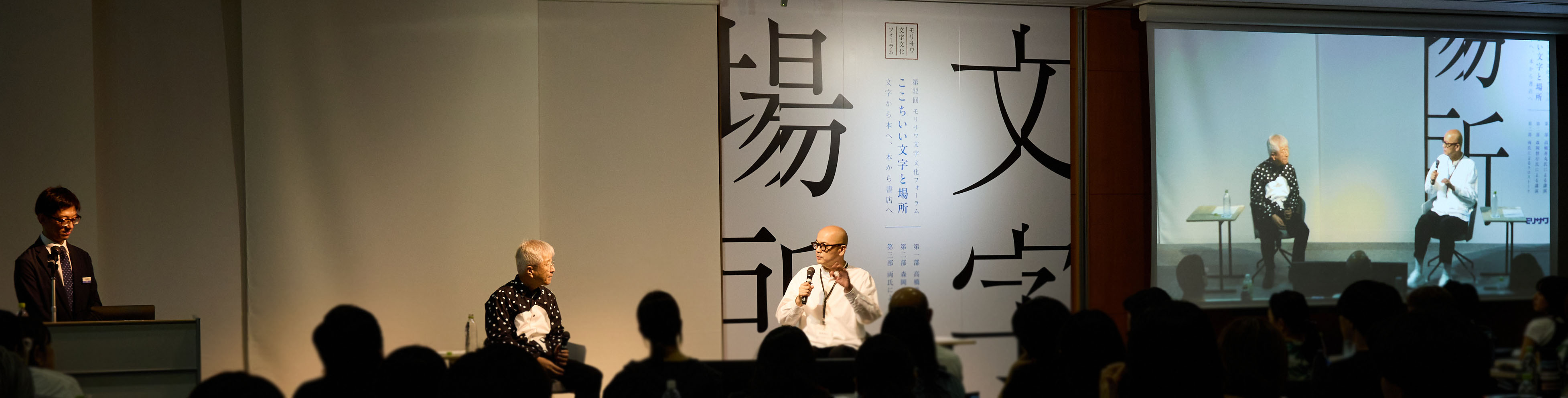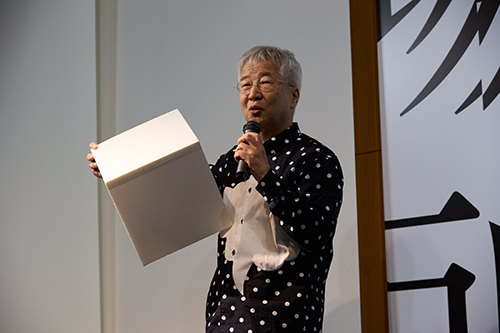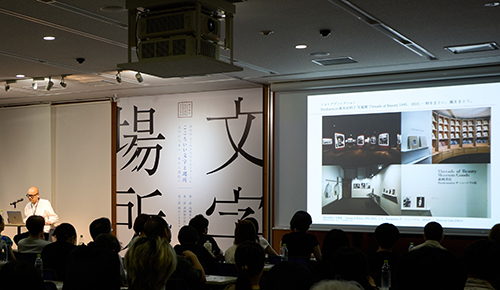
第32回モリサワ文字文化フォーラム 「ここちいい文字と場所 ―文字から本へ、本から書店へ」
2026年7月31日(金)、株式会社モリサワは第32回モリサワ文字文化フォーラム「ここちいい文字と場所 ―文字から本へ、本から書店へ」を開催。
エモーショナルなタイポグラフィを手がけるグラフィックデザイナー高橋善丸氏と「1冊の本を売る書店」をコンセプトとした森岡書店代表 森岡督行氏が登壇。
時を超え、空間を立ち上げ、人の心に鮮やかな情景を描き出す。そのリアリティはいったいどこに宿るのか。「文字デザイン」と「本」を起点に、人の思考や感覚を通して生まれる「ここちよさ」の本質を、独創的な視点から探る。新たな発見に満ちた密度の高いフォーラムとなった。
講演者
高橋 善丸(グラフィックデザイナー)
森岡 督行(森岡書店 代表)
第1部 高橋 善丸氏 「文字から、想像を促すデザインへ」
高橋氏は「文字から、想像を促すデザインへ」をテーマに据え、文字とビジュアルデザイン、2つの観点から話を進めた。
機能性・先進性・情感が生み出す文字表現
文字デザインの基本要素は読めること(可読性)をベースとし、そこに読みやすい形や安定した美しい形、長く読んでも疲れないといった「機能性」、新しさや独創性といった「先進性」、楽しさや表情などの「情感」の3つがバランスよく成立したところに「見て読んでここちいい文字」ができるという。
文字は情報を超えて情景を伝える
文字造形において、グリッドを基本としながら、線や交点の強調、有機的な曲線、文字の本質だけを残す簡略化などを取り入れることで、文字に意味や情景を与える表現を紹介。文字に感覚情報を加えることで、記号を超えた豊かな視覚表現が生まれる。「文字というのは理解のコミュニケーションツールだが、文字デザインというのは、感覚情報を盛り込むことで、記号性を遥かに超えた視覚情報が情景を伴って伝わる感覚のコミュニケーションである」と語った。
想像を促すデザイン
ここで本題に入っていく。
6面あるはずが実は3面しかない立方体や、白紙に雪を被った電柱を描くことで余白が雪原だと感じる作品を見せ、「情報をすべて与えなくても、想像のきっかけとなる要素があれば、見る側が頭の中で情景を補う」と語った。
「シンプルな表現でリアリティを出すとは、少ない表現要素で受け手の経験や既知の情報を引き出し、そこから多くのイメージを連想させることで、伝えたい内容をより豊かに広げる」。
さらに、一本の線やぼかした文字だけでも、人は地平線や奥行き、空間を感じ取ることができる。「リアリティというのは、写実的な映像を見せることではなく、どう相手の想像力を持ってリアリティを感じさせるか」と述べた。
想像を促すコミュニケーションデザイン
ここからは「想像を促すコミュニケーションデザイン」をテーマに、文字デザインによって見る人の想像力を引き出す手法や作品が紹介された。
二次元の文字から立体や空間を想像させた作品、影や水面の揺らぎによって時間や情景を連想させる表現、点や線、欠けた文字など、脳が最小限の情報を使って不足を補おうとする心理を利用した作品などが紹介された。さらに、「カニッツァの三角形」や「パレイドリア現象」などの視覚・心理効果を応用し、一つの作品に複数の意味を持たせる手法を解説。特定の視点からだけ文字が現れる「アナモルフォーシス」の技法を活用したインスタレーションでは、空間そのものをコミュニケーションの媒体にする可能性を示した。
高橋氏は、「相手の既知情報を利用し、イメージのきっかけを与えれば、脳に映像をつくりあげてくれる。はっきりと直接的な表現を避ける独特な日本的コミュニケーション方法を、私はグラフィックデザインで表現している」と語り、講演を締め括った。
第2部 森岡 督行氏 豊かさを伝えるための「1冊の本を売る書店」
森岡氏は「戦争や争いではなく、デザインや美しいものといった世界の豊かさに接続して生きたい」との思いから「1冊の本を売る書店」を始めた。毎週1冊の本を軸に展覧会を開き、著者や編集者、デザイナーと読者をつなぐ場をつくっている。
書店が入る東京・銀座の鈴木ビルは、かつて亀倉雄策らが活動した「日本工房」の拠点だった。その歴史に惹かれて入居し、ビルの住所を取り入れたロゴやオリジナル書体も制作した。
また、日本工房が句読点を省く誌面づくりを試みていたことを紹介し、文字デザインが試行錯誤された黎明期を振り返った。
人との出会いが未来をつくる
森岡氏は、展覧会の企画をきっかけに会いたい人へ自ら会いに行けることが仕事の醍醐味だという。著者や編集者、クリエイターとの出会いはすぐに成果につながらなくても、後に新たな仕事へ発展することがあり、その連続が「未来をつくる」と話す。
また、モリサワ創業者・森澤信夫が講演に感銘を受け、自ら星製薬の星一を訪ねた逸話を紹介し、自ら行動することの大切さを伝えた。
森岡書店では、1冊の本に合わせて店全体の空間をつくり変え、本の世界観を表現している。著者から人生や作品の背景を直接聞けることが、仕事を続ける原動力になっていると語った。
想像力が生み出す「ここちいい場所」
写真家ソール・ライターの蔵書を調査した際、本人が実際に訪れたことのない日本について、本の余白に「1972年に日本を訪れた」と書き込んでいたことを知る。
森岡氏は、その書き込みによって、頭の中で日本へ行ったかのような体験が作られたのではないかと推測し、胸を打たれた。
そして、高木由利子氏のモノクロ写真では、衣装や素材、色彩を鑑賞者自身が想像し、写真との対話が生まれるという。現実の場所でなく脳内で作られたものも、今回のテーマ「ここちいい文字と場所」と言えるのではないかと語った。
紙の文化の可能性
展覧会の世界観を丁寧に落とし込んだ12,000円の図録が約1,600冊売れたことを挙げ、紙の媒体には今なお大きな価値があると語った。デジタル化が進む一方で、日本には雑誌などの豊かな出版文化が根付いており、MoMAのキュレーターもその価値に注目しているという。紙媒体の衰退だけに目を向けるのではなく、その文化を大切に受け継いでいきたいと話した。
独自性が新しい価値を生む
「1冊の本を売る書店」は世界でも前例のない取り組みとして海外から注目を集めた。しかし、日本語の本を読めない来店客から「せっかく来たのに本を買えない」という声が寄せられた。そこで森岡氏は、本を購入した人に似顔絵を描くサービスを始めた。これがインフルエンサーの紹介をきっかけに話題となり、店の前に観光バスが横付けされるほどの人気を集め、中国での講演依頼にもつながった。
深圳での講演で「新しいアイデアはどのように生まれるのか」「イノベーションはどこから生まれるのか」と問われた森岡氏は、「自分が好きなことを徹底して続けることが、新しい価値を生むのではないか」と答えた。
デジタル時代だからこそ紙を読む
日本に帰国後、森岡氏は「新しいアイデアやイノベーションは、どこから生まれるのか」と改めて考えたという。その中で気づいたのが、紙の本を読むという体験の価値だった。
紙の本とデジタルの本は、脳の働き方や情報の受け取り方が異なるとされ、自身の実感としても、紙から得た情報のほうが身につきやすいと感じている。「AIやデジタルメディアがますます進化する時代だからこそ、逆に紙の本や文字、読めない文字に取り組むことで、自ずと新しさが生まれるのではないか」と話を締め括った。
第3部 クロストーク
対談は質疑応答も交え、それぞれのテーマでデザインや本の価値について語り合った。
「想像を促すデザイン」
森岡氏は、高橋氏の豊かな感受性や表現力の源を問いかけた。高橋氏は、色や素材を多用した時期を経て、要素を削ぎ落とし「造形と光」に表現を絞ってきたと語った。森岡氏は、長谷川等伯の「松林図屏風」が、平面でありながら奥行きのある空間として立ち現れた体験を紹介。高橋氏は、水墨画のように情報をあえて抑え、見る側の想像に委ねることで、より深い世界が生まれると説明。見る人の想像力を引き出し、より豊かな世界を生み出すという「想像を促すデザイン」の本質が語られた。
「寒河江百貨店のミニマムな空間」
森岡氏は、出身地・山形県寒河江市で、空き店舗となっていた旧百貨店を活用した「寒河江百貨店」をプロデュース。地方創生事業として実現したこの施設は、高校生が自習するカフェとして自然に定着し、地域の新たな居場所となり賑わいを生み出した。利用者が減少した商業施設も、視点を変えることで新たな価値を生み出せる可能性を示した。
「書籍にどう向き合っていくか」
高橋氏は、デジタル化が進む時代だからこそ、本というメディアの価値は失われないと話す。デジタルデータは技術の変化によって閲覧できなくなることがある一方、本は何百年経っても当時と変わらない形で手に取ることができる。絶版になった書籍が電子版よりかなりの高値で取引される例を挙げ、「人は知識だけではなく、感動そのものを所有したい」という思いが紙の本には宿っていると述べ、森岡氏も共感し深く納得した。
質疑応答
デザインが伝わるまでの時間について、高橋氏は、ポスターは3秒以内に興味を引くことを基本としながら、美術館などでじっくり鑑賞されることも想定していると説明。
デザイン提案の進め方について、高橋氏は、商業案件では複数案を提示しクライアントと納得し合える形をつくる一方、文化性の高いジャンルではデザイナー自身の表現や個性を重視すると語った。
「ここちいい文字と場所」の軸について、森岡氏は「今ここにいる人と時間を大切にすること」と語り、高橋氏は「ここちいい」というテーマを掲げた理由についても触れ、昨今のデザインは「新しさ」や「インパクト」が重視される一方で、人に寄り添い、長く愛されるというデザイン本来の役割が見失われがちではないかと指摘する。新規性だけを追い求めるのではなく、「心地よさを生み出すデザインの価値」を改めて見つめ直すことが重要だと語った。
最後に森岡氏は、高橋氏の新刊を書店で紹介したいと提案し、高橋氏も快諾。互いの活動を通じて「ここちいい文字と場所」をつくっていきたいという思いを共有し、フォーラムは締め括られた。